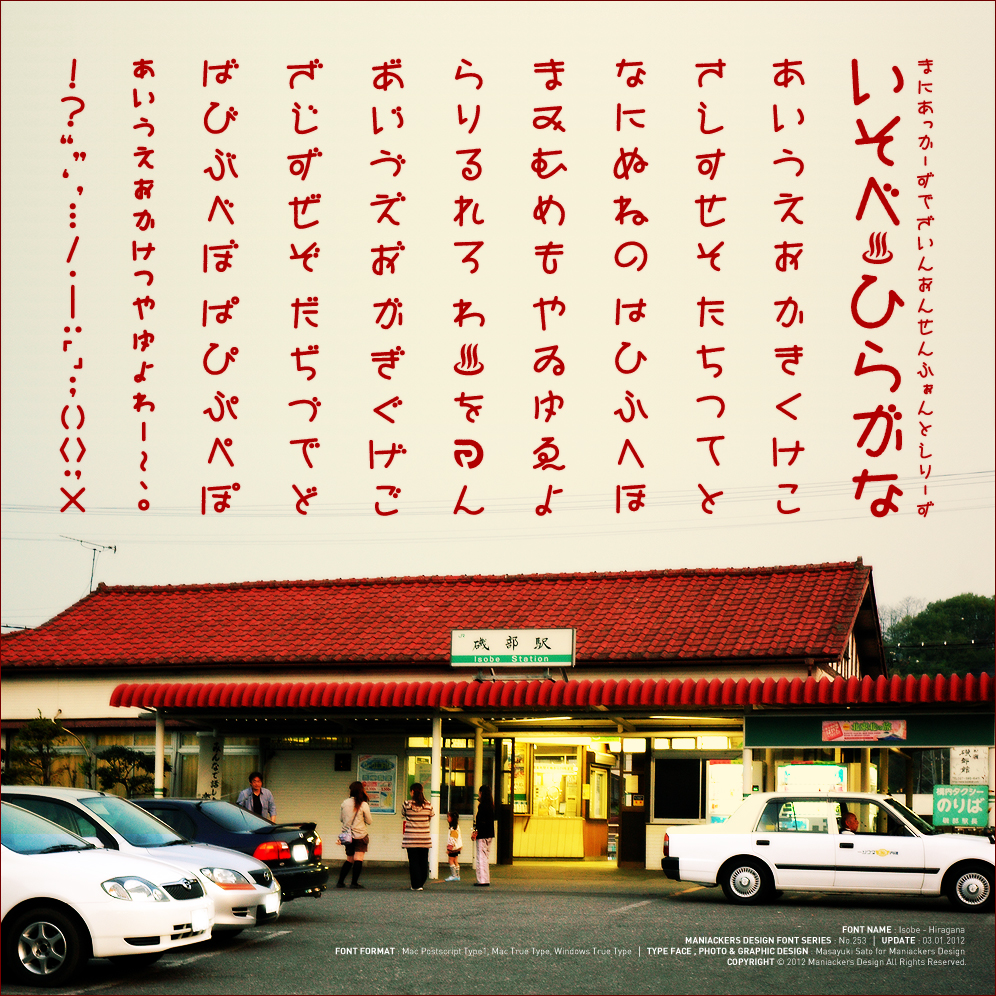
いそべひらがな
磯部温泉のイメージをモチーフにしたフリーフォント「いそべひらがな」。
かわいらしくユニークなフォルムのフォントで、レトロっぽさや落ち着いた雰囲気を感じさせる。線にガタガタした装飾がされていたり、濁点が丸いのもポイント。
♨は磯部温泉が発祥といわれている。
磯部温泉
群馬県安中市(旧国上野国)にある温泉。1661年に土地の境界をめぐる訴訟があり、このときに江戸幕府から出た判決文の地図に温泉記号が存在した。現在までにこれよりも古い使用例が見つかっていないことから、温泉記号(♨)発祥の地とされている。
明治の児童文学者・巌谷小波は舌切り雀の伝説が伝わるという磯部を訪れ、舌切り雀の昔話を書き上げた。おとぎ話自体は各地に昔からあるものの、巌谷小波が児童文学として現代に残したことで、磯部温泉は舌切雀伝説発祥の地とされている。